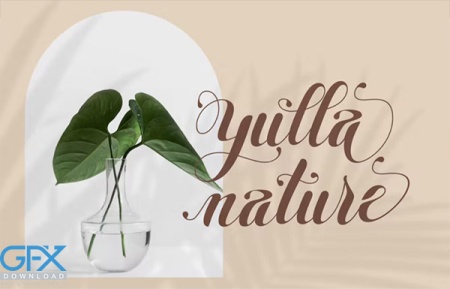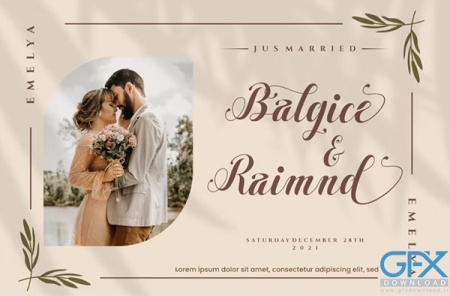
فونت خوشنویسی زیبا Emelya
فونت انگلیسی خوشنویسی زیبا Emelya
Emelya یک فونت اسکریپت خیره کننده است. به زیبایی طراحی شده و جزئیات بسیار بالایی دارد. این فونت خوشنویسی زیبا Emelya دارای کد PUA است که به این معنی است که شما می توانید به راحتی به همه حروف و swash ها دسترسی داشته باشید!
• نام فونت: Emelya
• لیگاتورها
• حروف بزرگ و کوچک
• شماره گذاری و علائم نگارشی
• پشتیبانی چند زبانه